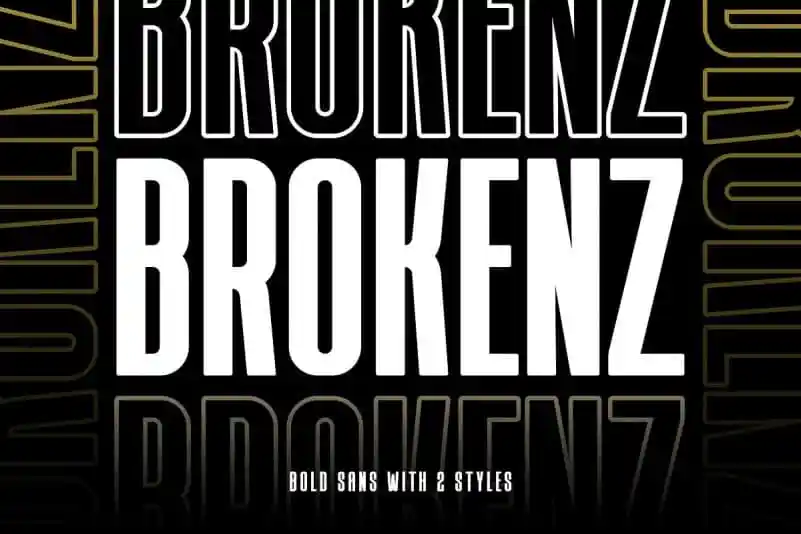
Brokenz – Bold Sans Serif Font – Download Grátis
Escolhendo a fonte “Brokenz – Bold Sans Serif” para seu próximo projeto? Você não pode estar mais no caminho com esta elegante e potente fonte. Construída para maximizar o uso de espaço horizontal, Brokenz é perfeita para títulos importantes ou nomes destacados. Este tipo forte e desafiador tem quatro estilos diferentes, criando nuances fortes e interessantes. Sua versatilidade se torna sua principal vantagem, tornando-a uma escolha óbvia não apenas para o título de seus projetos gráficos e editoriais, mas também para rótulos, texturas, revistas, brochuras ou embalagens. Seu design único é um choque de estilo moderno e profissional que certamente enriquecerá qualquer projeto. Brokenz – Bold Sans Serif Condensed oferece a perfeita mistura de elegância com eficiência, tornando-o um elemento crucial para o sucesso de seus projetos. Obrigado por conferir!